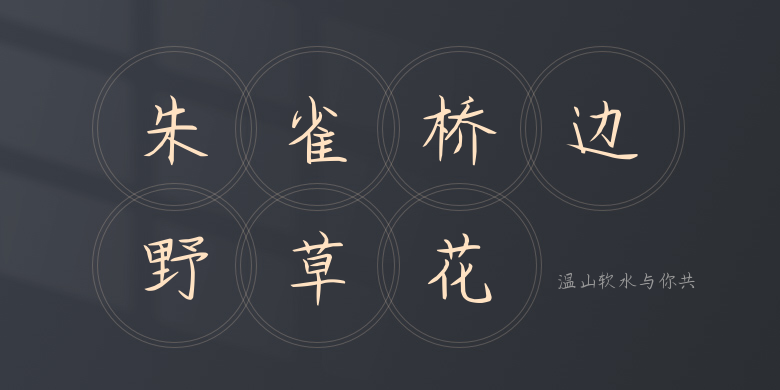
温山软水与你共
温山软水与你共,这款字体结构工整、笔画清晰,兼顾美观与易读性,适用于标题、正文、海报、包装、LOGO 等多种场景。字形优雅稳定,风格百搭耐看,适配日常排版与创意设计,让文字呈现更舒适、更具质感。温山软水与你共一笔一画,皆是细节,以均衡的比例、流畅的线条打造舒适视觉体验,字形端正大气,风格简约现代。无论是商业设计、品牌宣传还是日常排版,都能轻松驾驭,让文字更有格调与力量。温山软水与你共字体下载。